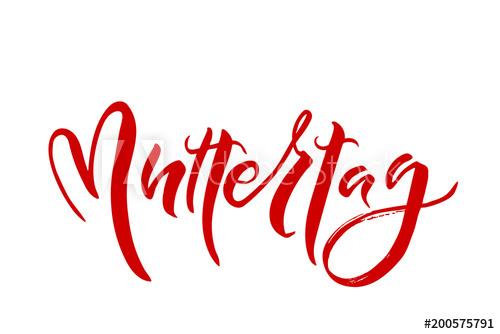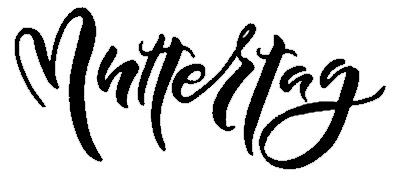
Suche Schriftart aus einer Werbung für den Muttertag
Hallo zusammen, ich Suche nach der Schriftart von einer Werbung für den Muttertag aus einem Werbeprospekt einer Bäckerei. Gefunden in einer Werbeprospekt Aussendung an alle Haushalte. Ich hoffe ihr könnt mir weiterhelfen, mit besten Grüßen Highlander
Mit hoher Wahrscheinlichkeit wurde das Wort nicht aus einer Satzschrift erzeugt. Die fehlende Grundlinie, die unterschiedlichen „t“s, die „er“-Buchstabenverbindung und das zu gut passende herzförmige „M“ sprechen eher für Handlettering.
Das ist laut dem Gestalter "hand drawn" und bei Adobe Stock käuflich zu erwerben: